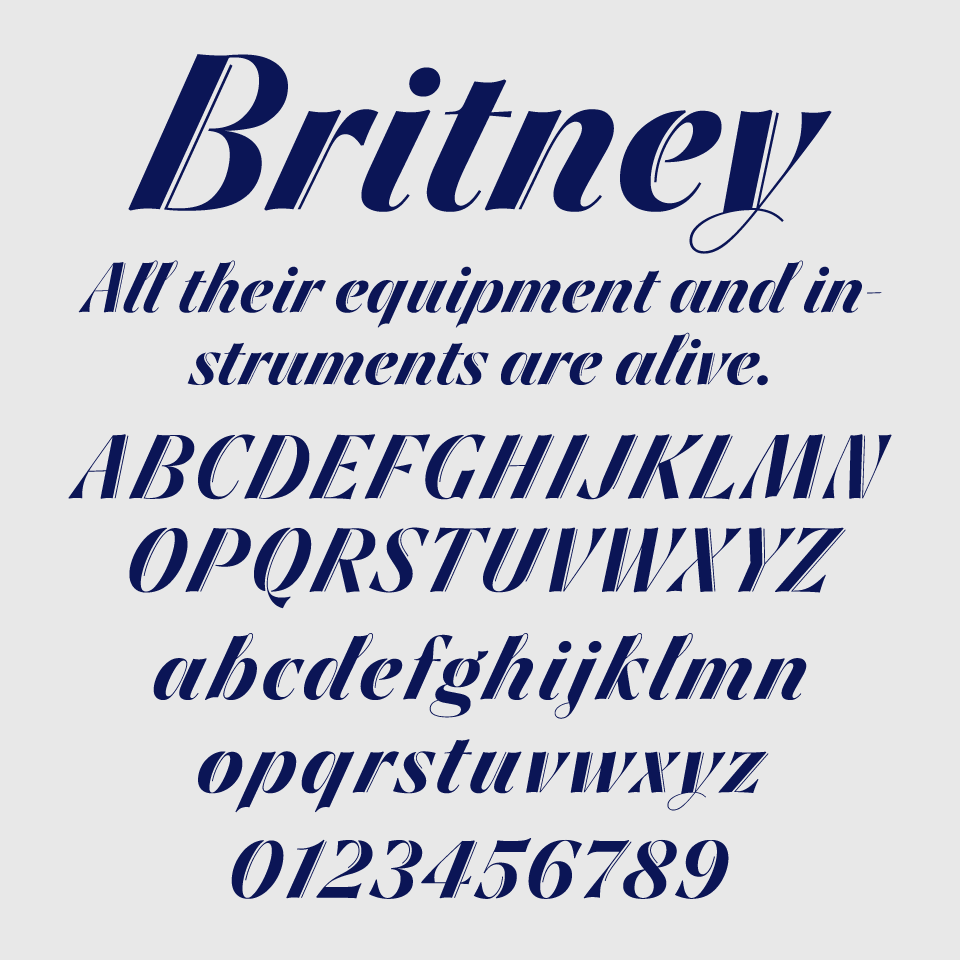
Britneyフォントは、優雅な傾斜と繊細な縦線が印象的なモダンなイタリックセリフ体です。
まるでファッション誌のロゴのように、洗練された雰囲気と動きのあるリズムを感じさせます。特に筆記体風の小文字や、2重のラインの重なりの曲線的な大文字のあしらいがエレガントでとっても素敵なフォントです。
スタイリッシュで都会的な印象があり、美容・コスメ系、ラグジュアリーなブランドなどのトーンにぴったり。だけどフォーマルながらも遊び心を感じるディテールが、個性を引き立ててくれるフォントです。